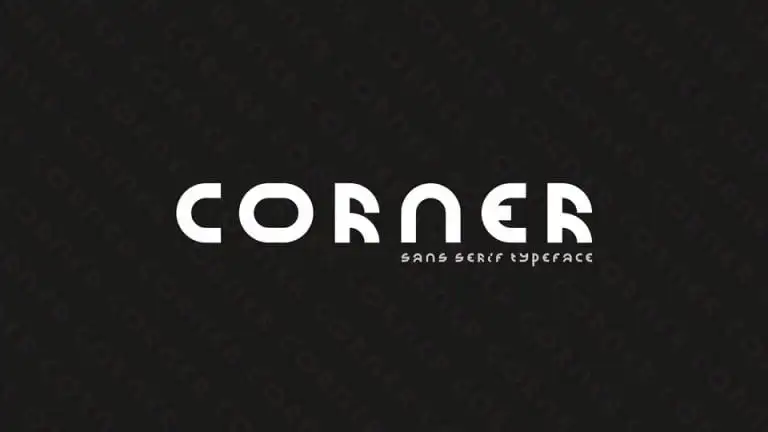
Introduzimos a Corner Display Font, uma tipografia tipo grande que combina elegância e modernidade. Ela é fruto do talento de Olivier Tavernier, disponível neste marketplace de design online. Esta tipografia modular geométrica apresenta um aspecto único, perfeitamente adaptado para várias aplicações gráficas. Suas linhas definidas se destacam em materiais visuais como cartazes e capas de álbum, mas também são ideais para vídeo games, subtítulos de notícias e mensagens poderosas. Atrativo, versátil e moderno, Corner Display Font é uma excelente escolha para quem procura uma fonte de exibição que se destaca e faz a diferença em qualquer projeto gráfico.